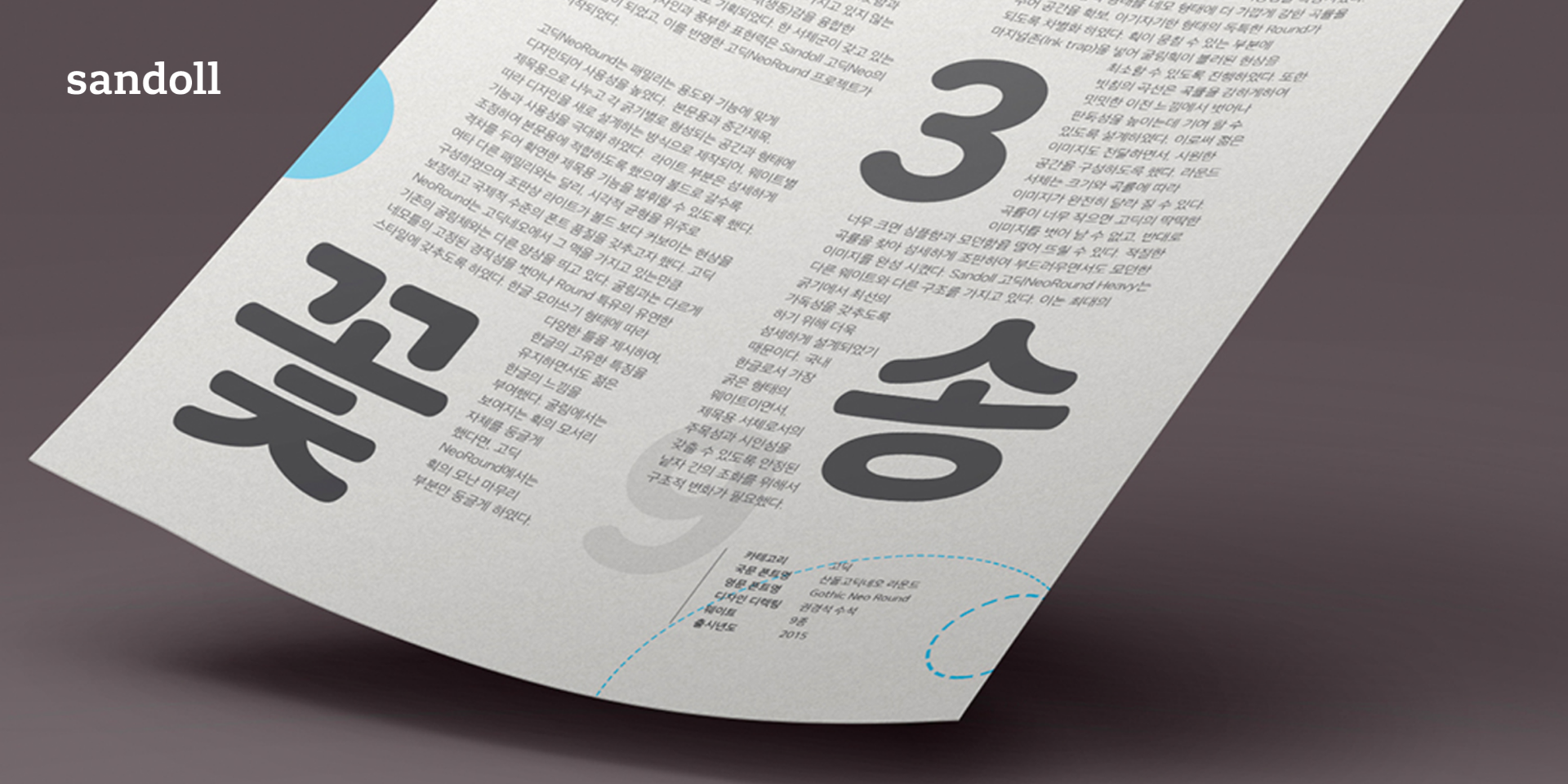
Sandoll 고딕
NeoRound
산돌 고딕NeoRound는 2011년 출시된 고딕Neo1에서 출발한 다섯 번째 프리미엄 본문용 폰트이다.고딕의 강점인 깨끗함과 심플함은 유지하면서 고딕에는 없는 부드러움과 생동감을 나타낼 수 있는 스타일로 제작되었으며 웨이트에 따라 본문용부터 제목용까지 두루 활용할 수 있다.